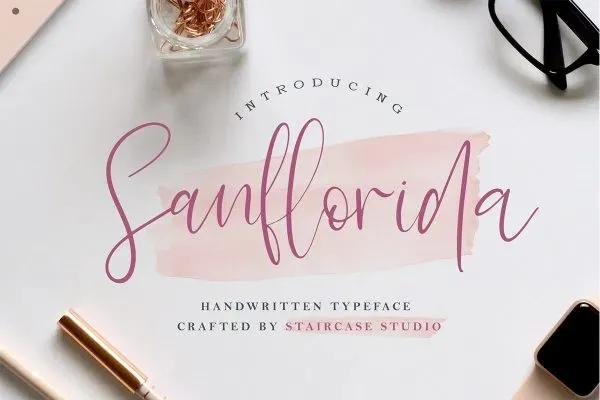
A Sanflorida Font é uma elegante tipografia script desenvolvida pela StairCaseLab com influência da escrita à mão. Essa fonte perfeita para os projetos digitais, especialmente agradável tanto para logotipos quanto para desenhos de marca e logomarcas. Sujeito ao seu uso em design digital, cria uma letra viva que se adapta perfeitamente para aplicativos como camisetas e adereços, materiais impressos para posters, revistas, sinalizações, publicidade e qualquer necessidade de design. A Sanflorida é a escolha ideal para aqueles buscando uma tipografia com a qualidade e personalidade que tanto valorizamos em nossos projetos gráficos.